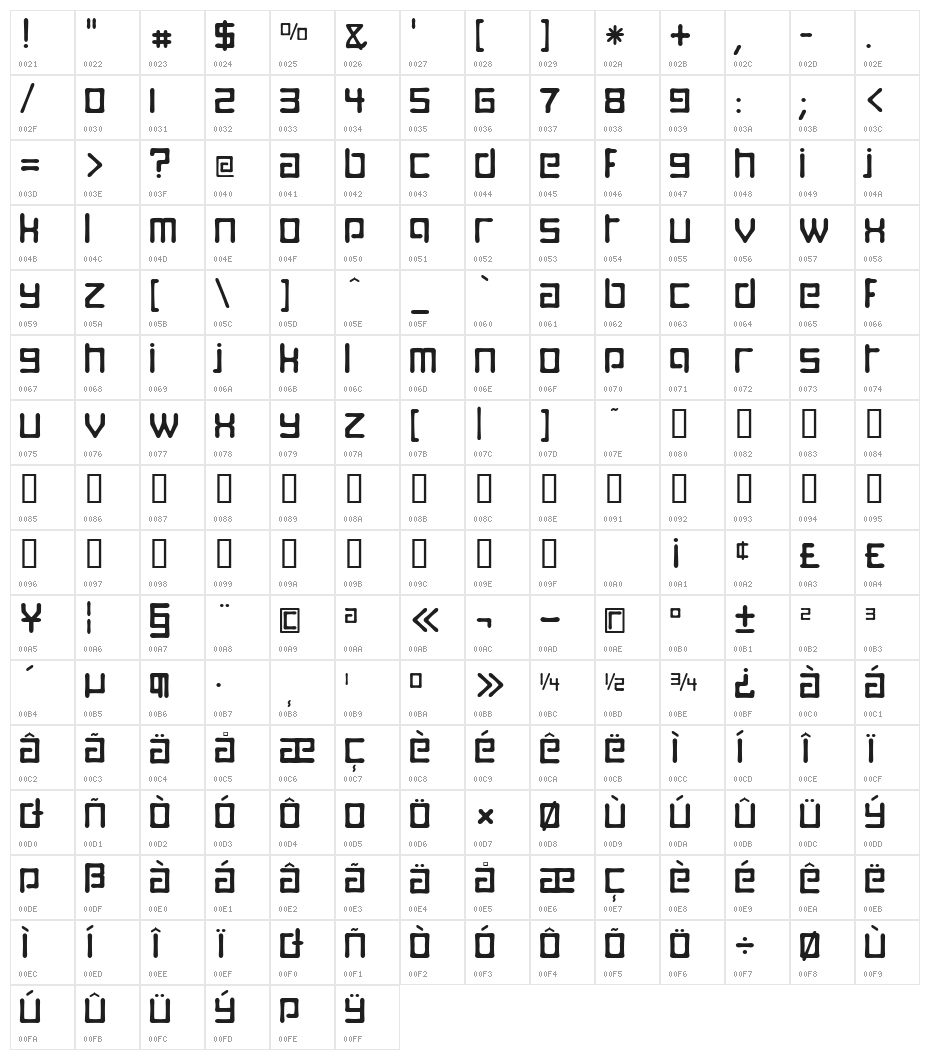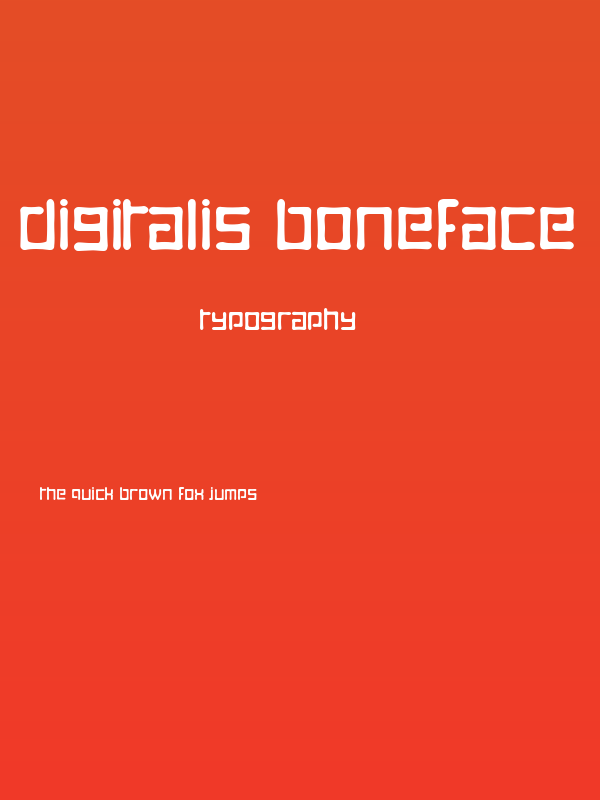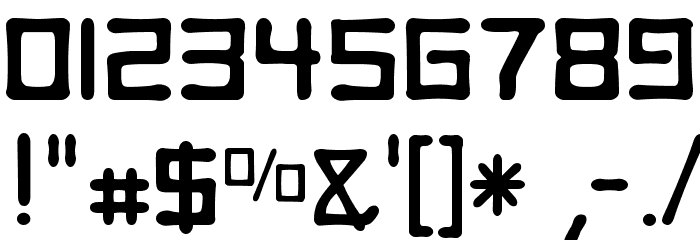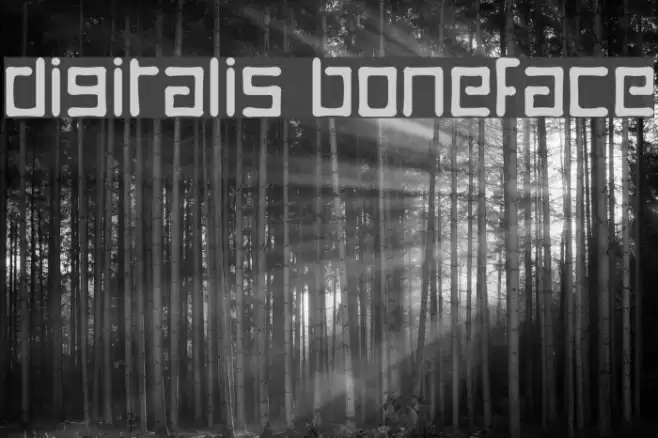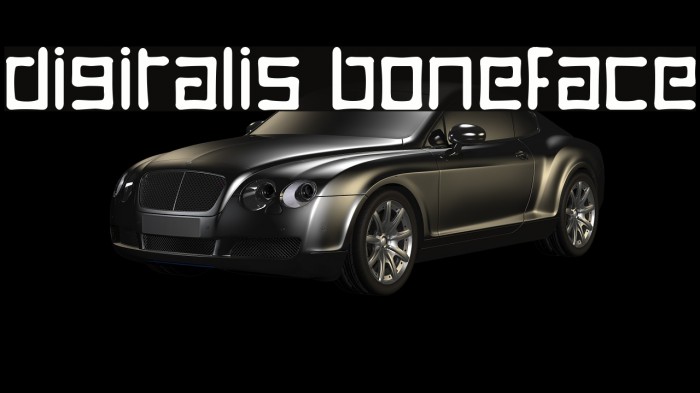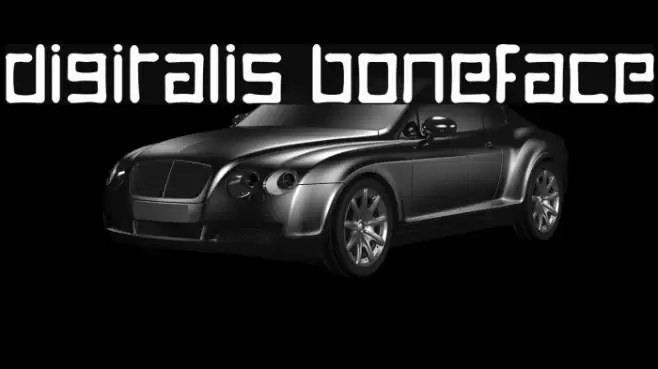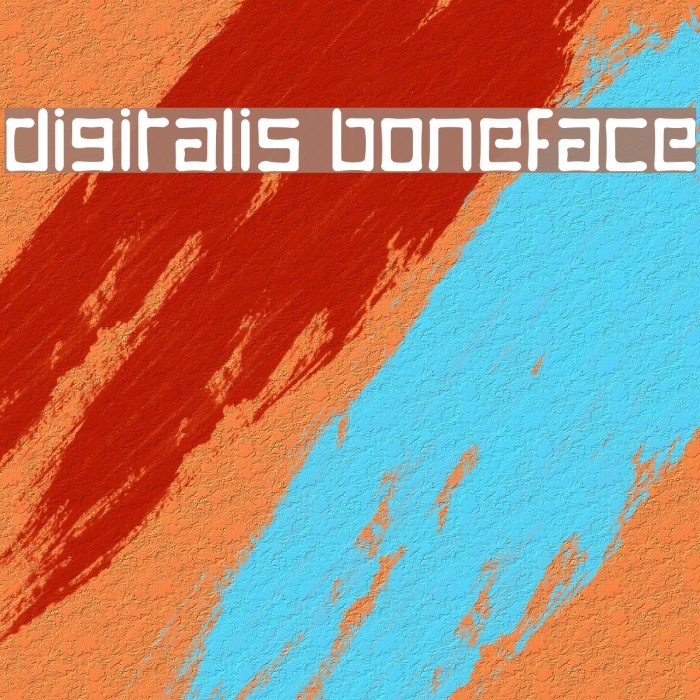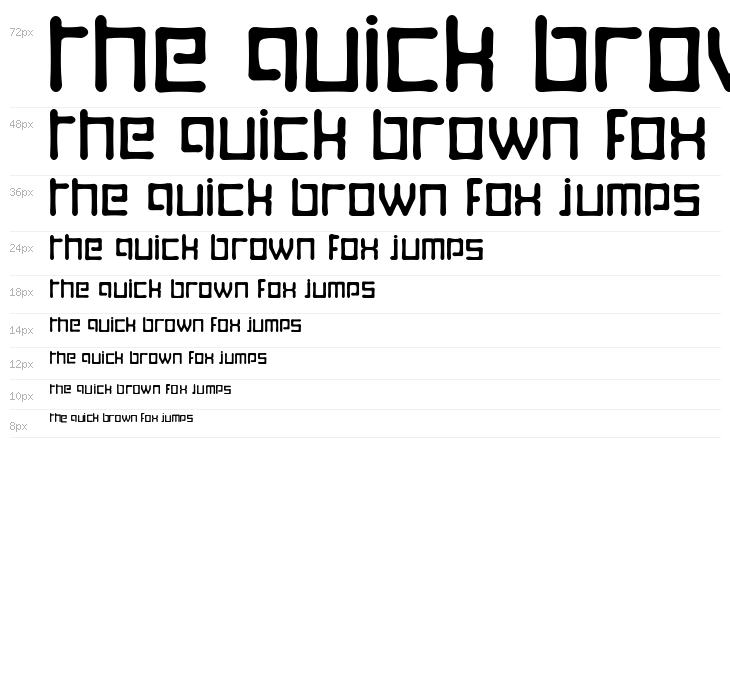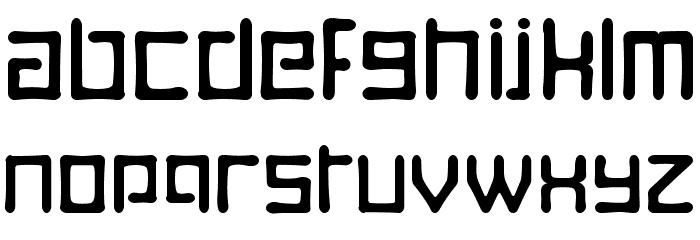
Digitalis Boneface Font
DIGITALIS-BONEFACE 大文字
DIGITALIS-BONEFACE 小文字
DIGITALIS-BONEFACE その他の文字
| 用途 | Headlines, Logos, Branding |
| おすすめプロジェクト | Ideal for branding, advertising, packaging, and digital media projects that require a modern and approachable aesthetic. |